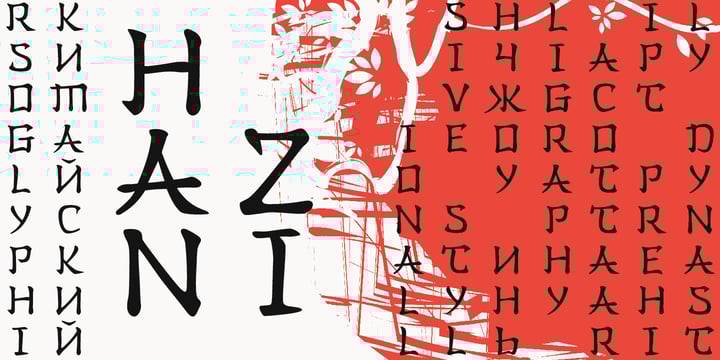
В китайском стиле шрифты: 30 шрифтов в китайском стиле
Смешение китайского и западного текстов
Дизайнеры иногда сталкиваются с проблемой работы со смесью языков. Это особенно распространено в таких местах, как Гонконг, где китайский и английский языки считаются официальными.
Эти засечки могут быть прямыми или изогнутыми и придают шрифту ощущение элегантности.